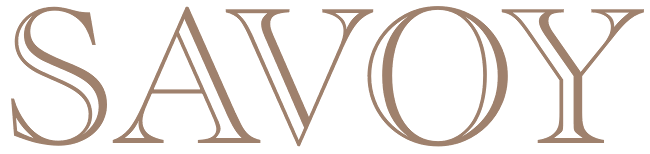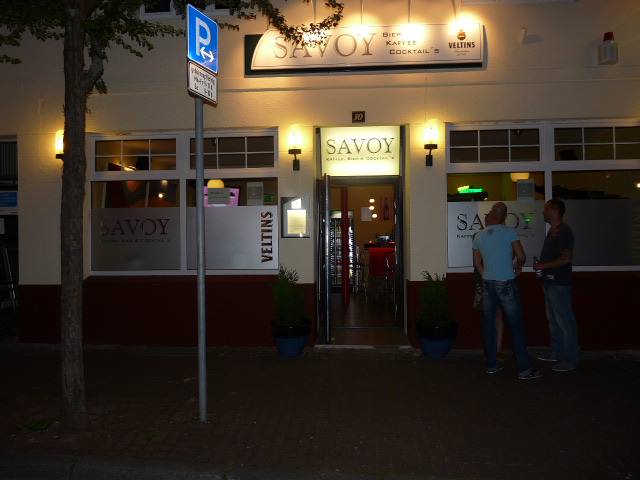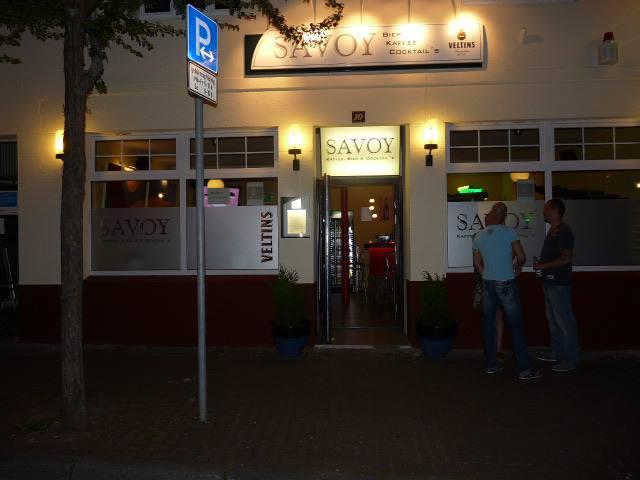
Suche die Schriftart von dem Schild.
suche die Schriftart von dem Kneipen Schild. Hoffe könnt es erkennen. Die Besitzer haben der Werbefirma schon geschrieben, leider brauchen die ewig und wir wollen Flyer gestalten.
Hm, das Bild ist jetzt nicht so deutlich, aber ich würde mal auf Caslon Openface tippen:
Fals der Querstrich beim A doch nicht doppelt ist, könnte es auch die hier sein: